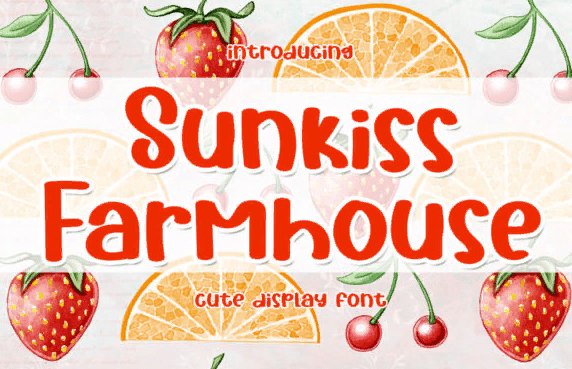
Название: Sunkiss Farmhouse Font (2021)
Sunkiss Farmhouse - это веселый и дружелюбный шрифт, который может легко выделиться.
Простой, но с сильным визуальным эффектом, этот шрифт мгновенно сделает ваше творение более привлекательным, чем любое другое.